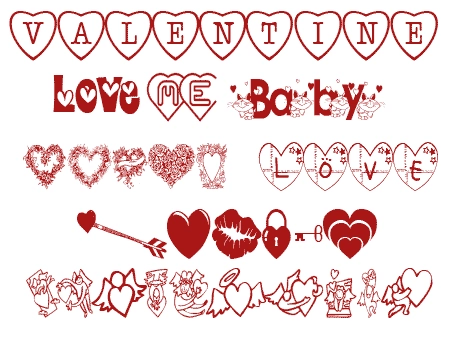
Великолепный шрифт для создания романтических открыток! Этот уникальный шрифт предлагает возможность написать свои пожелания и слова на английском языке. Но это не все: в некоторых стилях шрифта буквы заменены на прекрасные иллюстрации, которые придают открыткам еще больше очарования и индивидуальности.
Вы можете без стеснения использовать этот шрифт, чтобы порадовать своих близких и любимых людей! Ведь с помощью него вы сможете создать неповторимые и оригинальные открытки, которые запомнятся надолго и принесут радость и улыбки вашим близким.
Дайте волю своей фантазии и создайте авторские открытки, которые будут отражать вашу любовь и заботу! Выбирайте нужный стиль шрифта, сочетайте его с изображениями и создавайте уникальные композиции, которые точно понравятся вашим родным и близким. Имейте в виду, что этот шрифт доступен только на английском языке, но это не помешает вам выразить свои чувства и эмоции в самом прекрасном виде.
Не упустите возможность порадовать своих близких и любимых уникальными и неповторимыми открытками! Используйте данный шрифт и дарите радость с особым стилем и творчеством.